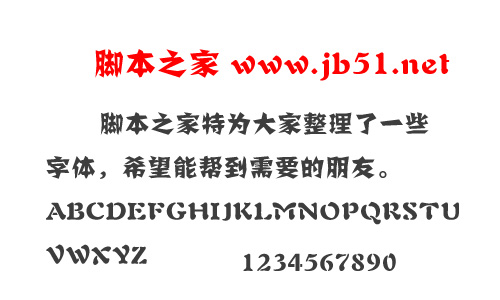
方正剪紙簡(jiǎn)體字體是方正字體庫(kù)中的一種字體,方正剪紙取材于中國(guó)民間的剪紙藝術(shù)。這款字體將剪紙中特有的“連”、“錯(cuò)位”等手法轉(zhuǎn)變?yōu)樽煮w構(gòu)成的元素,造型洗練,筆畫(huà)靈活多變,筆筆如剪,剛健挺拔。方正剪紙的風(fēng)格淳樸,富有濃郁的鄉(xiāng)土氣息和節(jié)日氣氛,是一款裝飾性極強(qiáng)的創(chuàng)意字體,適用于傳統(tǒng)節(jié)日的海報(bào)設(shè)計(jì),以及傳統(tǒng)類(lèi)品牌的廣告和產(chǎn)品包裝設(shè)計(jì)。喜歡的朋友們可以前來(lái)下載使用。